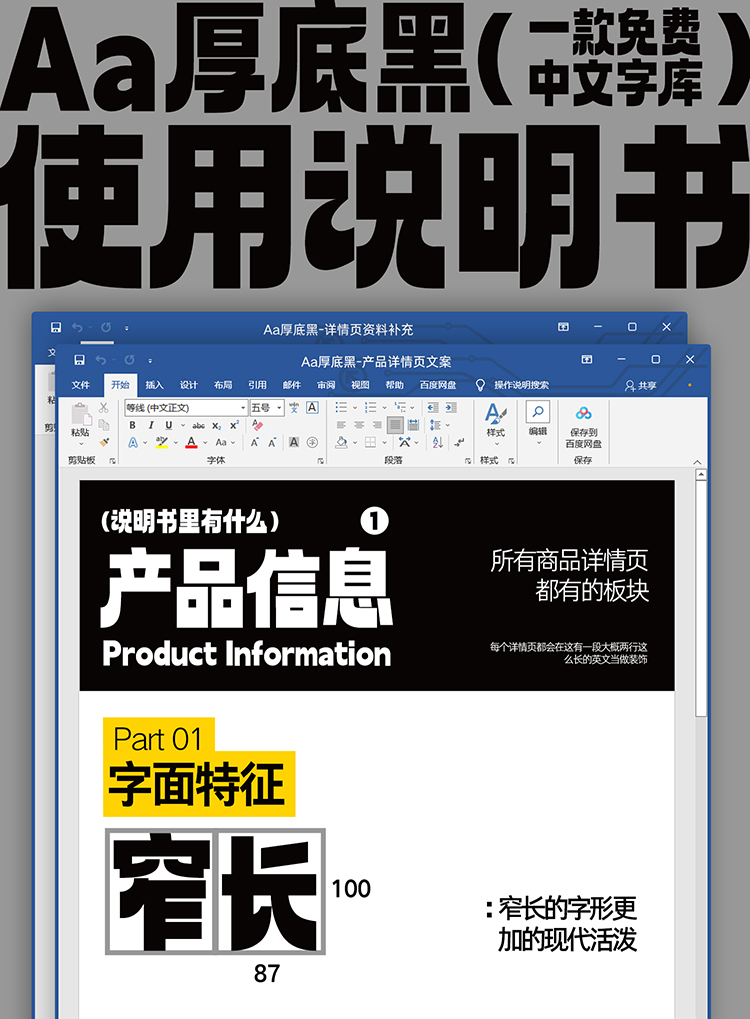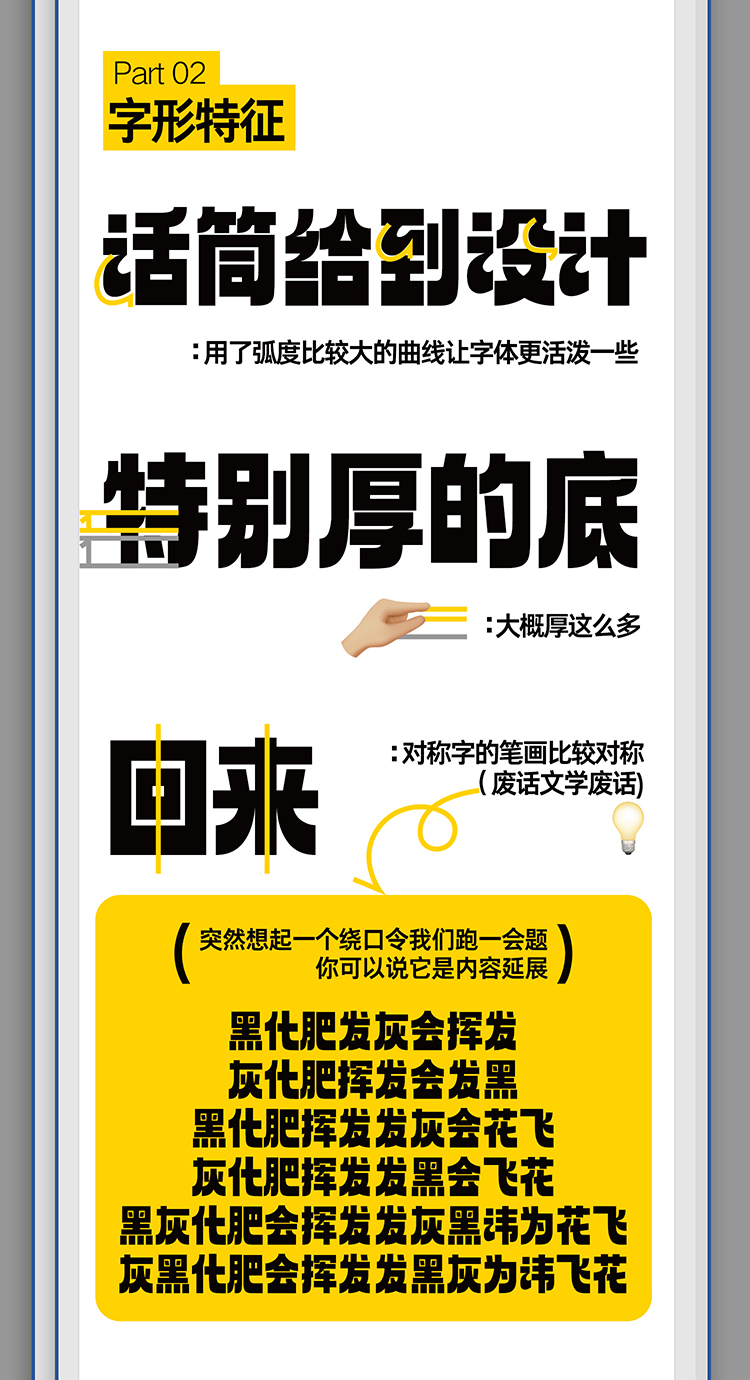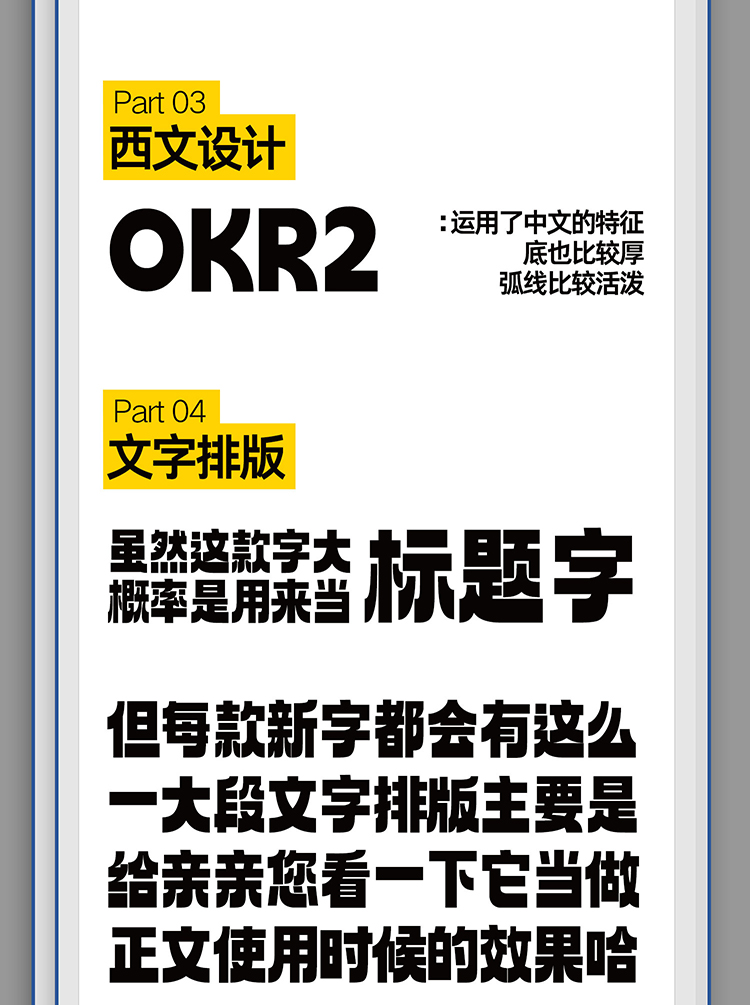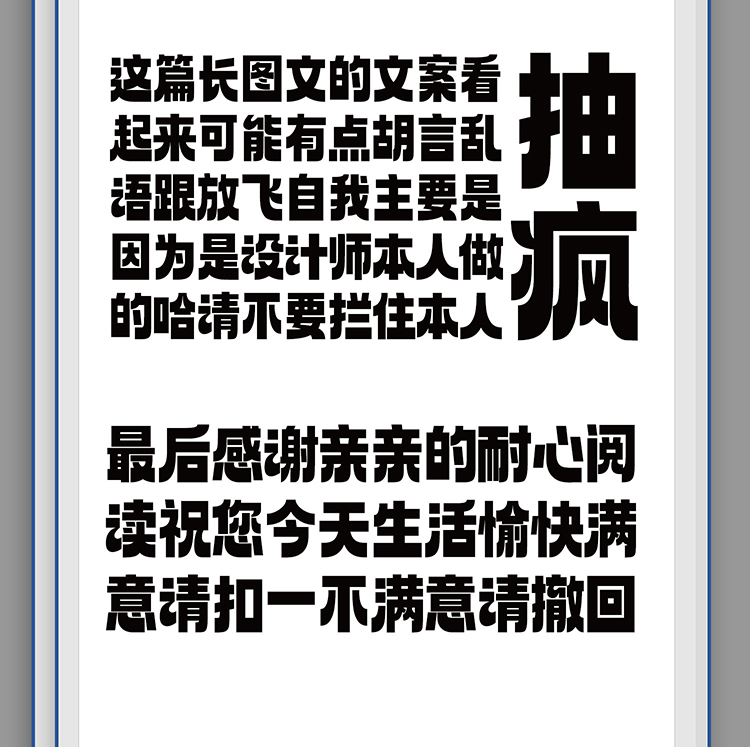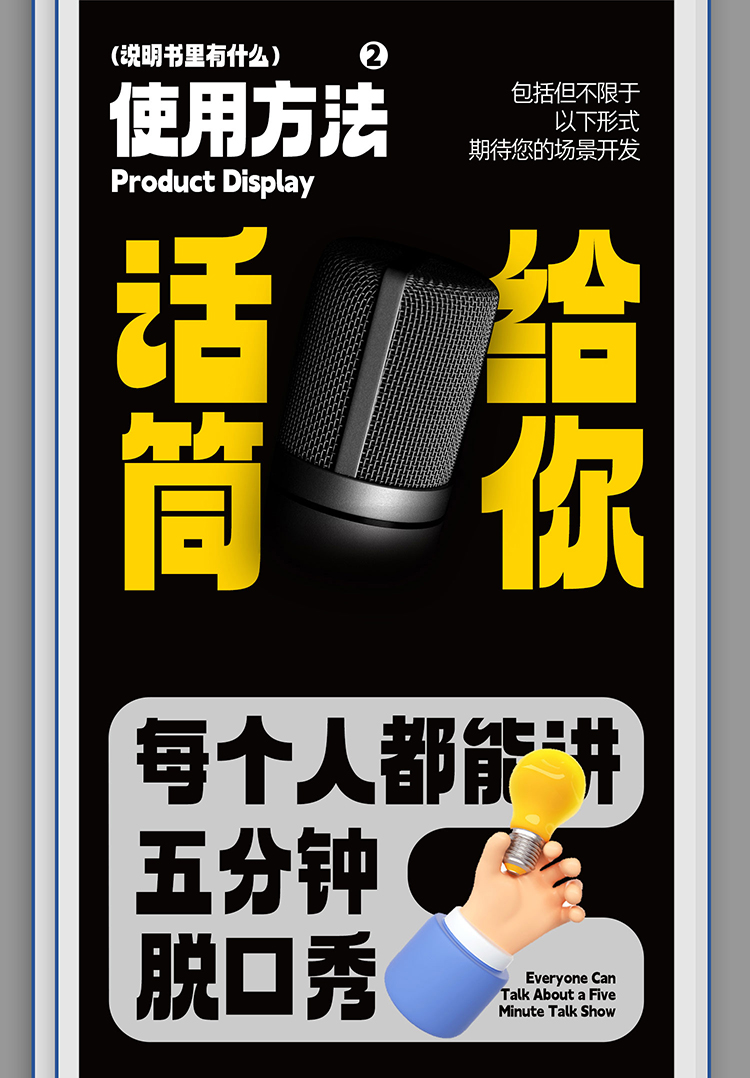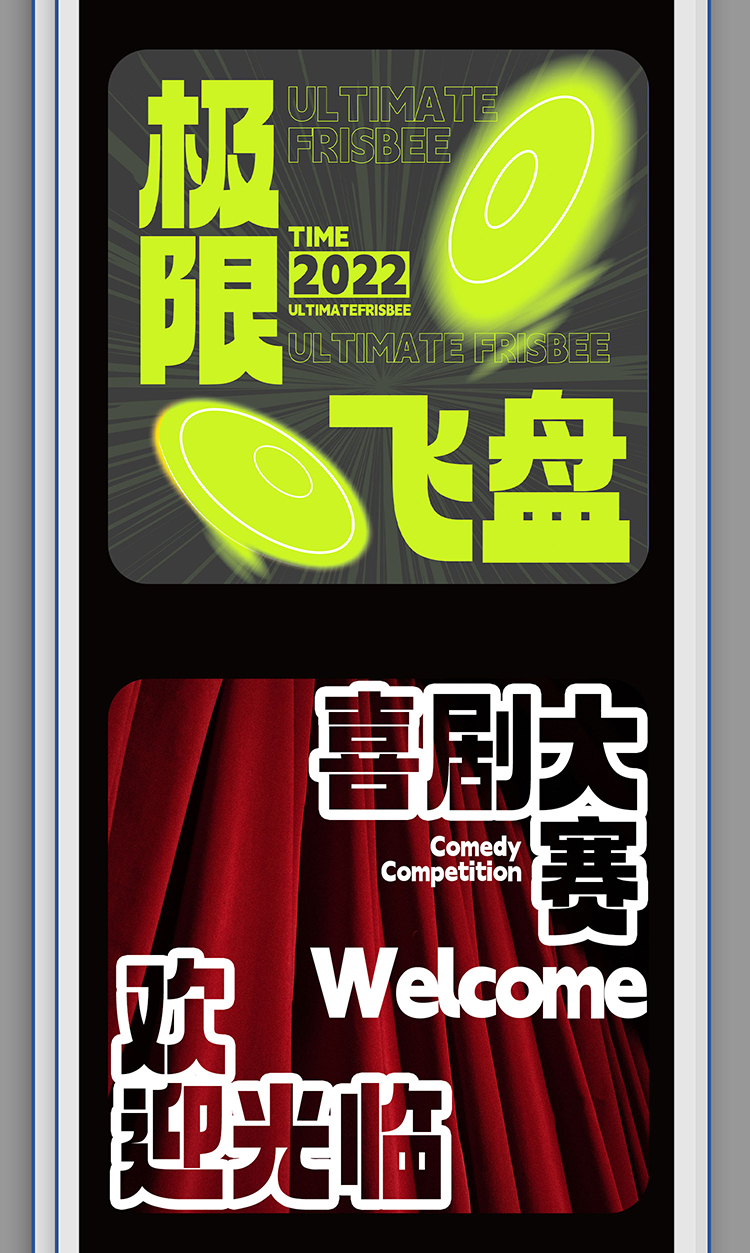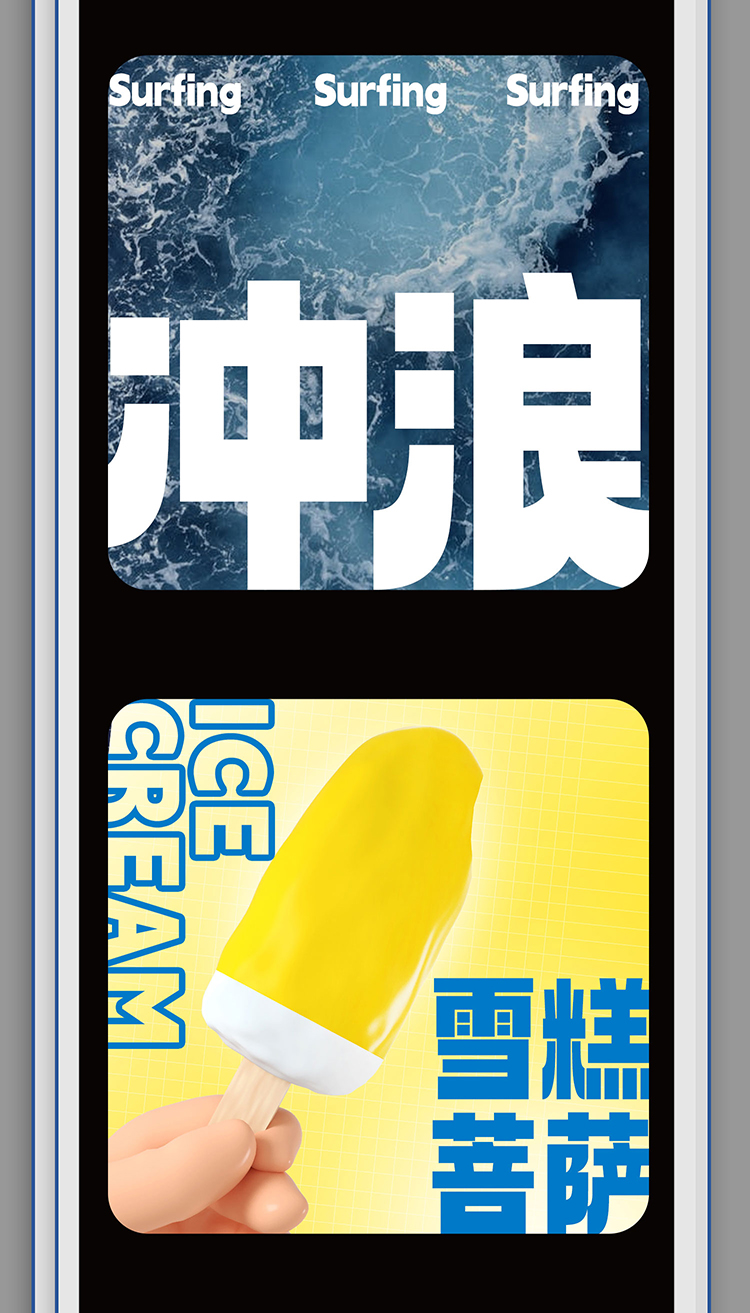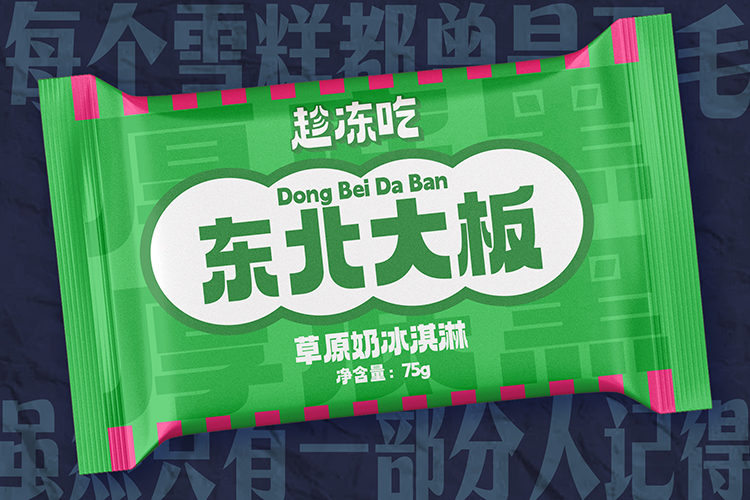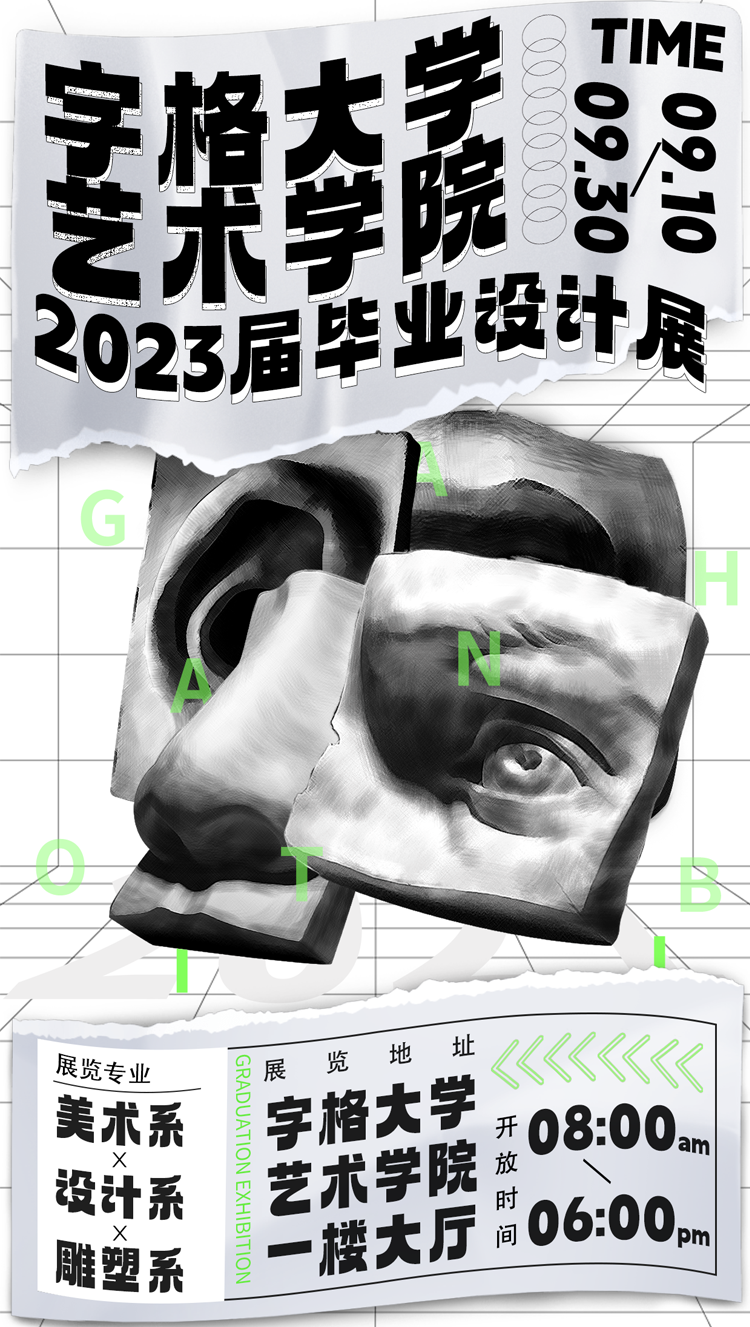
Aa厚底黑
字体说明:Aa厚底黑字体是一款可商用的毛笔书法,英文手写,手写体字体,该字体包含6763个中文、字母、符号和数字,具有充满力量、大气、豪放、稳重、手写风、古典 的风格,可以满足您设计上的各种需求,该字体主要用于电商、广告、视频影视、海报企宣、书籍 等场景, 您不但可以在字格网下载Aa厚底黑,同时还有众多毛笔书法字体、创意字体等可供选择!